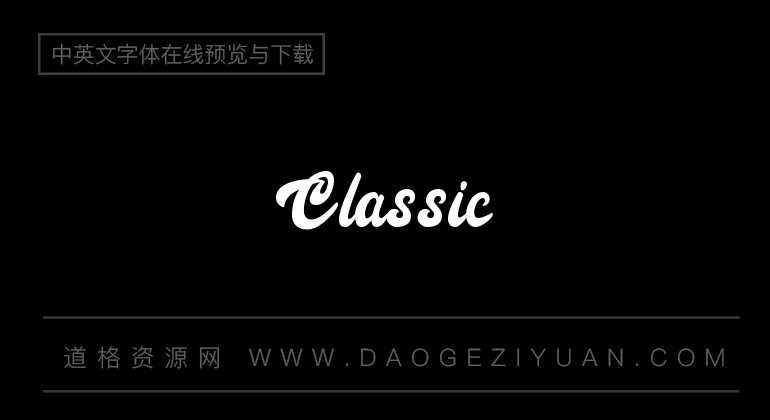
Classic
Classic 字体是一种新的技术字体,它可以帮助您更好地阅读文本,更好地呈现文本,更加清晰,更容易识别。它可以让您更好地控制文本的大小、字体、行距、字符间距等,从而获得更好的文本体验。Classic 字体也可以使您的文本更加美观,更容易读取,更有吸引力。
Classic是一款非常不错的手写艺术字体,具有很好的视觉感,适合于文化类的宣传设计、商业类品牌的广告和产品包装设计以及个性化文字排版等较多场景。